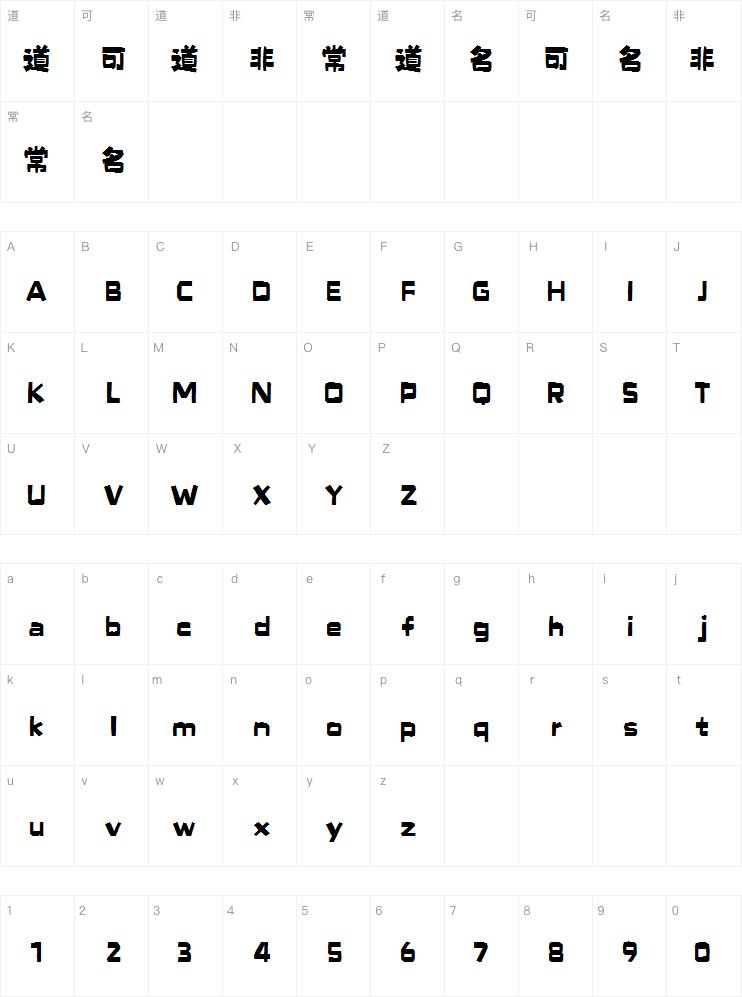
山海木头人,是一款全新的字体,包含汉字9169个,符号200+个。该字体是一款卡通风字体,该字体字形灵动多变,童趣可爱,在灵动的同时而又极富俏皮感。在粗细的纵横间,拥有非常规的自由灵动特性。笔画间的关系密不可分,同时也增加了字体的自由洒脱之感。每个笔画的造型类似木头剪影,结构多变灵动,字形活泼清新,造型生动有趣,具有灵活的适用性,天真俏皮又不失时尚感。该字体字形随笔画多少、结构布局不同而大小不一,各个字的大小随字形的不同而呈现不同的大小,但是在变化中寻求平衡,使得整个字体更具有温度和节奏感。灵动笔画贯穿笔画始终,内涵丰富,弧度柔和,撇笔平缓舒展,尽显俏皮灵动。